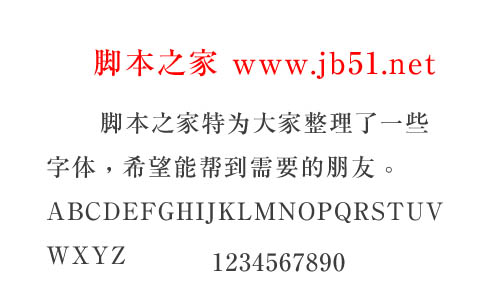
民國報(bào)紙字體是一款以民國報(bào)紙上的字體為原形而設(shè)計(jì)常規(guī)中文字體,字體粗細(xì)適中,整體效果非常的出色,能夠適用于藝術(shù)設(shè)計(jì)、包裝印刷、簽名設(shè)計(jì)、圖形設(shè)計(jì)等領(lǐng)域,歡迎有喜歡或需要此字體的朋友們前來下載使用。